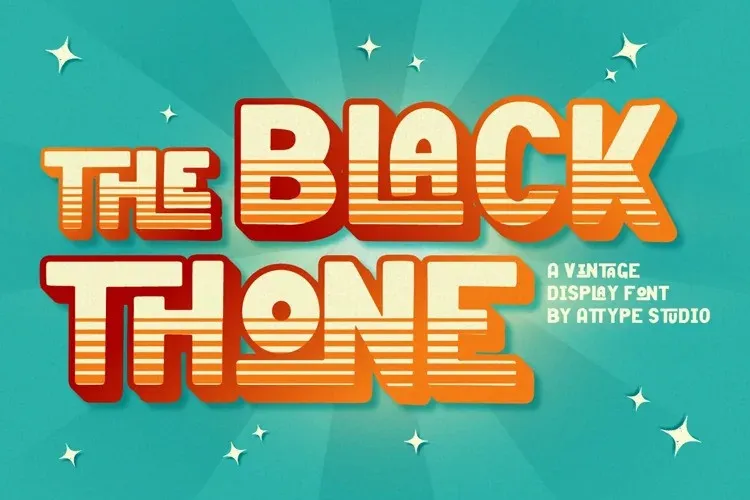
A Black Thone Font é uma tipografia de display ideal para logotipos, criada por Attype-Studio inspirada na época dos anos 70. Esta fonte apresenta um estilo vintage e retro que encanta os olhos, com três estilos disponíveis para maximizar a personalização. A Black Thone oferece facilidade no uso de efeitos tridimensionais, uma característica muito útil especialmente em ambientes digitais modernos. Com sua versatilidade e estilo único, ela é perfeitamente adaptada para criar um impacto visual marcante em qualquer design. Este fonte da categoria Display Fonts, oferecida por 99designs, é uma excelente escolha para quem procura uma solução de tipo que seja tanto funcional quanto estética.